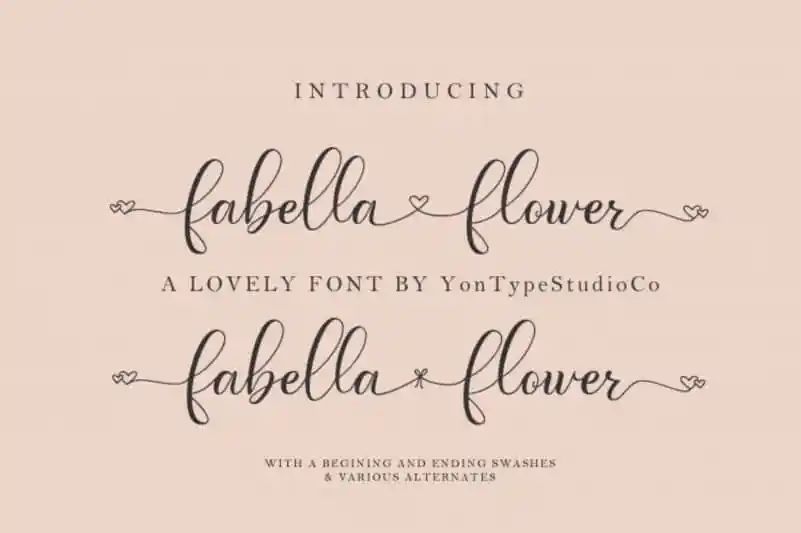
Fabella Flower Calligraphy Font – Download Grátis
A Fabella Flower Calligraphy Font é uma elegante caligrafia que brilha nas marcas de marca, convites de casamento e projetos românticos. Suas linhas fluidas e detalhes suaves a tornam perfeita para qualquer projeto exigindo um estilo personalizado, como convites de casamento, cartões de agradecimento, cerimônias de casamento, cartas de cumprimentos, logotipos e muito mais. Essa fonte é ideal para quem deseja dar um toque especial e único aos seus trabalhos, tornando-a uma escolha perfeita para aqueles que querem destacar-se no meio de uma produção que exige estilo pessoal. Engajante e sofisticada, a Fabella Flower Calligraphy Font se destaca como uma opção imprescindível para qualquer designer gráfico buscando uma caligrafia floral única e encantadora.